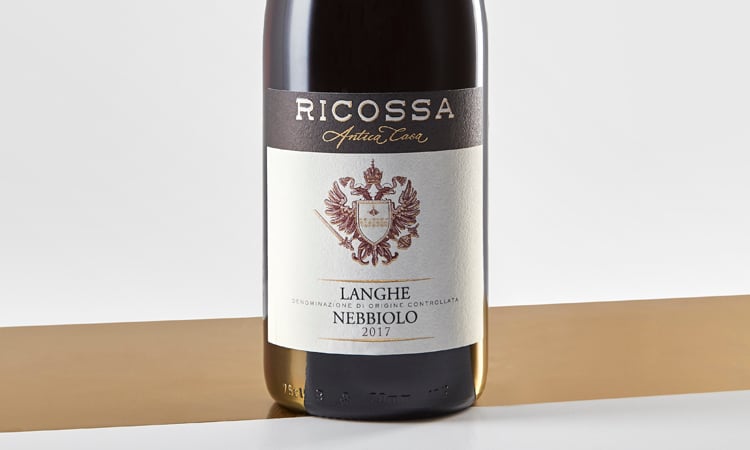
# Etichette per bottiglie di vino: i colori e i font più adatti!
##### Che sia sullo scaffale di un supermercato o tra le pagine del vostro e-commerce, la vostra bottiglia di vino ha bisogno di un’etichetta che sia in grado di catturare immediatamente l’attenzione del potenziale cliente e, al tempo stesso, comunicare i valori che contraddistinguono il vostro brand.
La concorrenza, si sa, è sempre più alta: le **etichette per bottiglie di vino rosso** devono essere attraenti e rassicuranti, fornendo al consumatore indeciso tutte le informazioni di cui potrebbe avere bisogno.
Vediamo quindi insieme come scegliere i colori e i font più adatti per comunicare efficacemente l’unicità del vostro prodotto e i valori della vostra azienda.
### Etichette vino eleganti o innovative?
La prima cosa di cui tenere conto se si vogliono stampare **etichette per bottiglie di vino rosso** è, naturalmente, il colore della bottiglia stessa. Il vino rosso, infatti, viene venduto in bottiglie di colore molto scuro, generalmente verde o marrone, per prevenire l’ossidazione causata dai raggi solari. È quindi consigliabile scegliere un’etichetta su **sfondo bianco o molto chiaro**, che risalterà maggiormente. Per quanto riguarda gli elementi grafici, invece, i colori andranno scelti ponendo particolare attenzione al target di riferimento e al posizionamento del prodotto sul mercato.
![etichette per vino rosso](https://www.oppaca.com/hs-fs/hubfs/Imported_Blog_Media/etichette_classiche_rett-1.jpg?width=750&height=450&name=etichette_classiche_rett-1.jpg)
Se volete creare **etichette per bottiglie di vino rosso** che abbracciano i principi dell’agricoltura biologica e biodinamica, suggeriamo colori naturali. Il verde, che richiama subito l’idea di “prodotto green”, ma anche tutta la gamma cromatica dei marroni e dei beige che ricordano l’elemento terra.
Un vino rosso che si pone invece in continuità con la tradizione del territorio avrà bisogno di mantenere uno stile altrettanto tradizionale, con **etichette vino eleganti** con un design dal carattere vintage e calligrafico in bianco e nero o con pochi colori tenui. Consigliata anche l’aggiunta di pochi dettagli dorati che, oltre a donare una nota di classe, conferiscono l’idea di una bottiglia pregiata.
Al contrario, un’azienda vinicola giovane e innovativa potrà osare con colori bold, intensi e vibranti, e accostamenti inediti: dal rosa shocking all’ottanio, dall’ocra al verde brillante, largo alla fantasia e alla creatività!
### Font per etichette: come scegliere il migliore per il tuo vino
Una volta stabilita la palette cromatica dell’etichetta sarà necessario scegliere il **font migliore** per il vostro prodotto. Il **font per etichette** dovrà, come il colore, essere in linea con il brand e rispondere alle necessità del consumatore. Un font illeggibile, infatti, difficilmente spingerà all’acquisto.
È consigliabile scegliere una **coppia o un trio di font** in base alla posizione e alla funzione del testo nell’etichetta. Per le informazioni obbligatorie, come la natura merceologica o il nome e la sede dell’imbottigliatore, l’ideale è un font condensed e ben leggibile come Calibri, Frutiger o Futura, indipendentemente dal tipo di vino e di azienda.